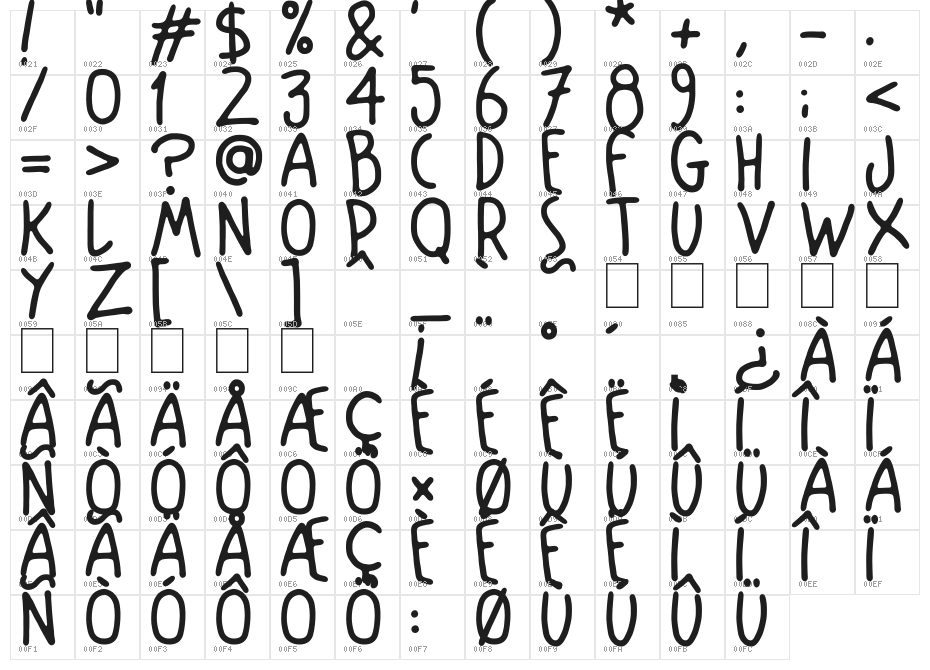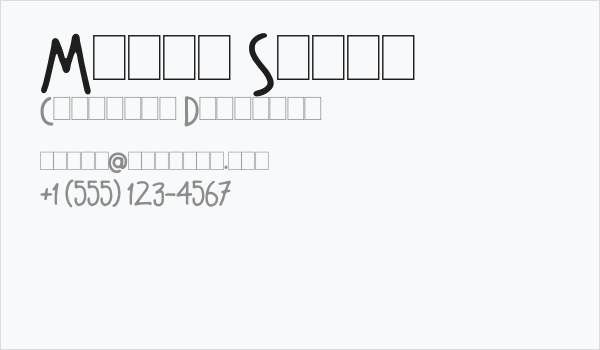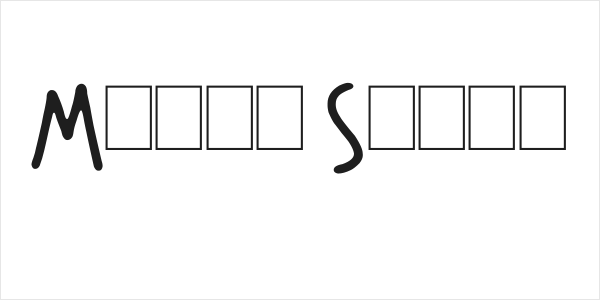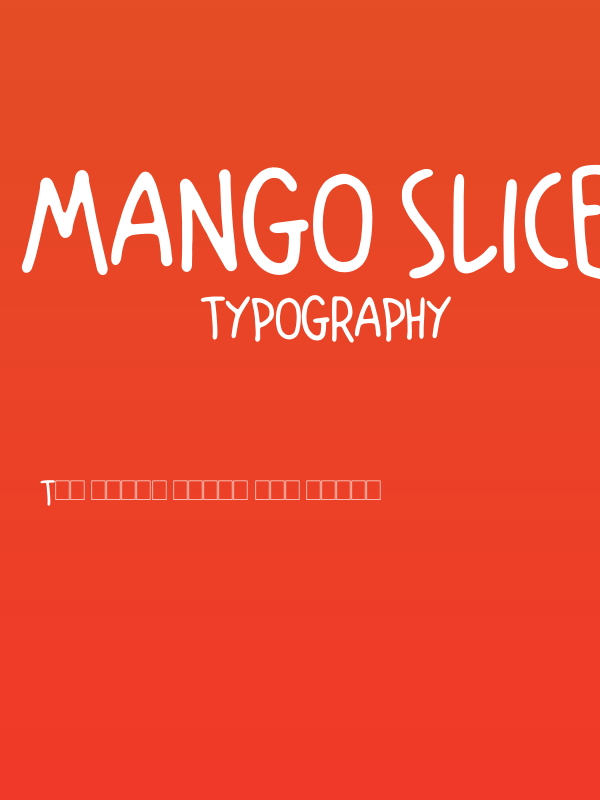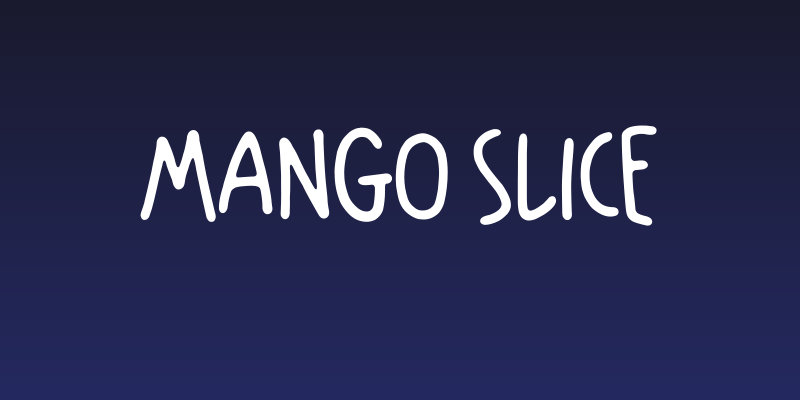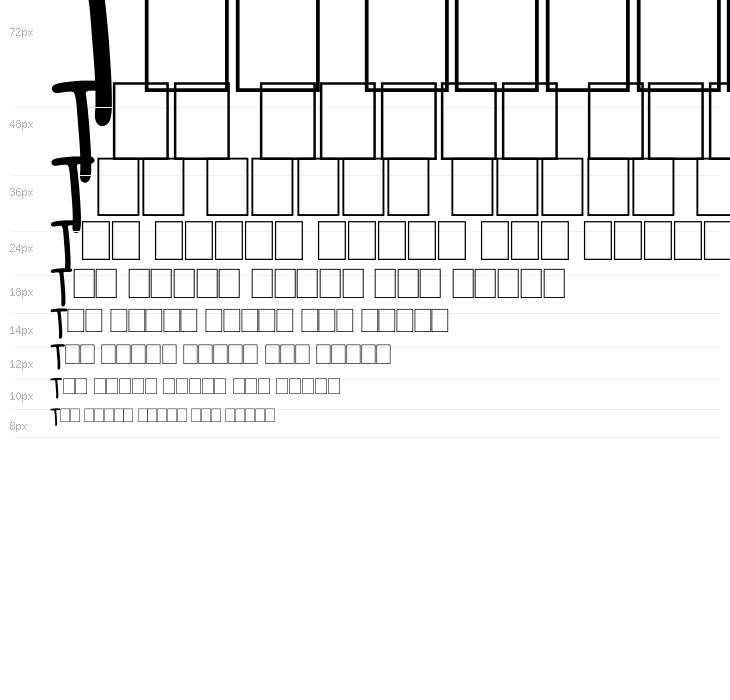
Mango Slice Font
| Общий стиль | Playful |
| Область применения | Headlines, Logos, Informal Text |
| Рекомендуемые проекты | Ideal for children's books, greeting cards, playful branding, and any project needing a fun, lively touch. |